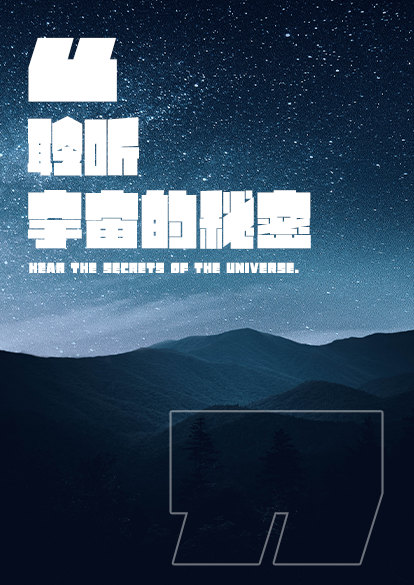
潮流逆反差字体——励字大头黑,开启字体进化之旅
励字大头黑是来自2077年的未来探险家,他生活在汉字宇宙中,追求深入探究汉字宇宙的本质和规律。
他的好奇心和热爱驱使着他不断前行,不满足于表面的现象,而是追寻知识的无穷魅力和力量。他驾驶着飞船,穿越星际,探索未知的星球和异次元空间。
他是一位充满魅力和智慧的角色,外形如同变异的超能者,有巨大的头,字体内部重心失衡上移,笔画则打破传统规则,粗细组合不均,转折处以直角处理后,形成的一款横平竖直、右侧笔画厚重、左边笔画极细的逆反差直线字体。用自己的行动向世界证明了知识的无限可能性。
励字大头黑的存在为整个汉字宇宙注入了新的活力和神秘感,他的探索之旅永不止步,引领着我们走向未来。